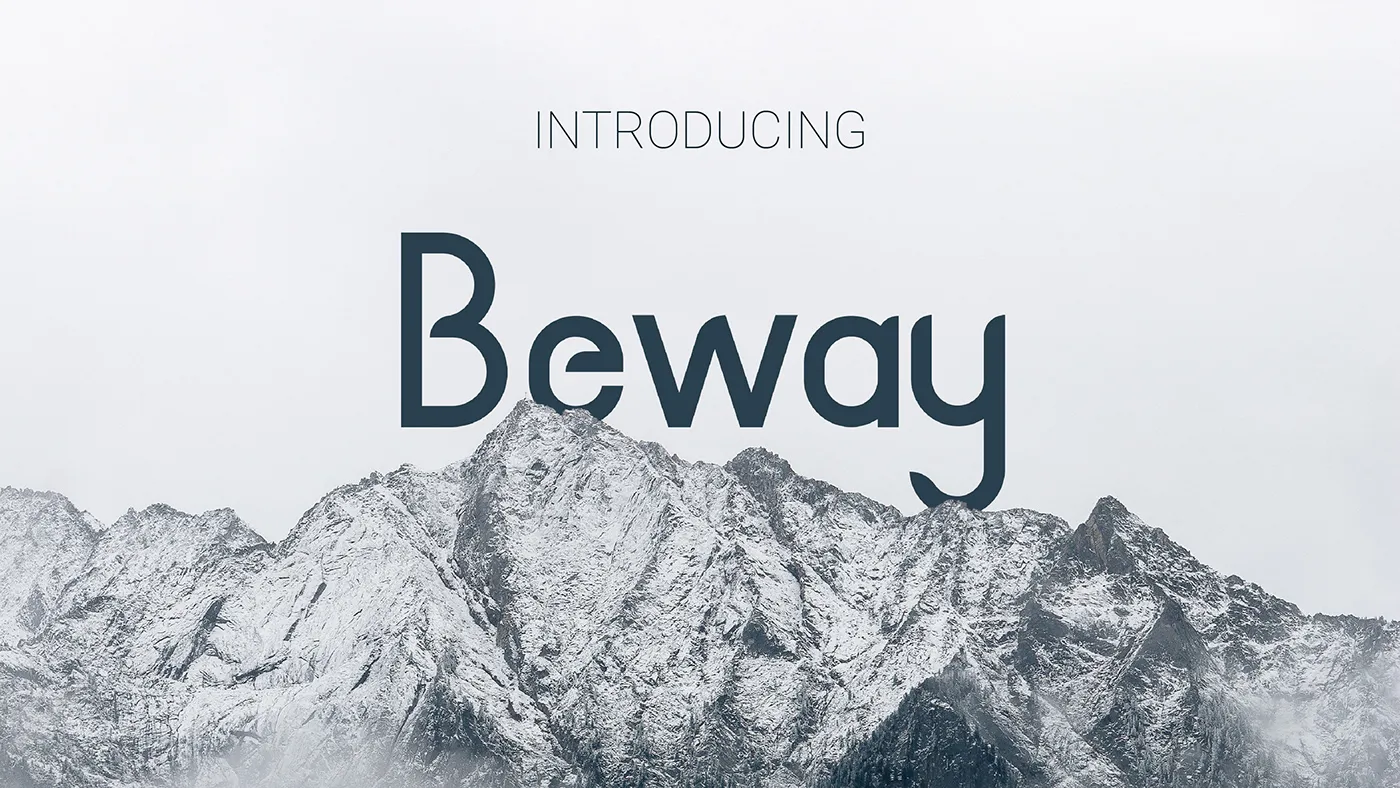
A Beway Typeface é uma elegante e ágil fonte ideal para aplicativos que exigem um toque de sofisticação, seja ela em cartões de visitas, marcas de marca, revistas ou até mesmo em anúncios e mensagens pessoais. Ela combina linhas contrastantes, perfeitamente adaptadas para qualquer projeto visual que você esteja planejando. É uma fonte “A Little”, o que significa que possui um toque especial que torna suas criações ainda mais únicas e marcantes. Seja em um cartão de visita profissional ou na capa de sua revista, a Beway proporcionará aquele toque de beleza e sofisticação necessários para destacar seu trabalho. Feitas para serem usadas em diversos formatos e cenários, seja uma marca de sucesso ou simplesmente uma mensagem pessoal, a Beway oferece um ar de elegância que combina perfeitamente com qualquer projeto. Ela é uma fonte de uso amplo que pode ajudá-lo a tornar seu design visual mais impactante e memorável. Assim, você pode criar algo belo hoje, fazendo da Beway uma escolha ótima para qualquer projeto de design gráfico em sua lista de tarefas.